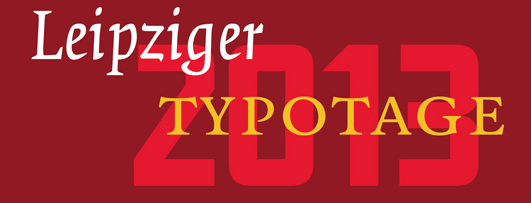
Noch vor weniger als zehn Jahren waren die typografischen Möglichkeiten in den Online-Medien begrenzt. Neue Geräte wie Smartphones, Tablet-PCs und e-Books und mobile Anwendungen wie Apps eröffnen der Typografie nun ungeahnte und vielfältige Möglichkeiten. Aber auch im Bereich der Schriftgestaltung hat das neue Jahrtausend schon einiges bewegt, junge Typografen denken und verwenden Schriften anders, ob in animierter Form, als digitale Redesigns historischer Vorbilder oder entwickeln ganz individuelle Designs für analoge und digitale Anwendungen.
Die verschiedenen Spielarten von Typografie im Spannungsfeld zwischen Print- und Onlinemedien heute wollen die 19. Leipziger Typotage näher beleuchten. Eingeladen sind acht renommierte Referenten, die über unterschiedlichste Projekte berichten und damit gleichzeitig die Trends in der Typografie im frühen 21. Jahrhundert beleuchten.
Die Referenten
Tim Ahrens, Berlin
David Fichtmüller, München
Friedrich Forssman, Kassel
Maurice Göldner, Leipzig
Christoph Knoth, Berlin und Halle/S.
Prof. Stephan Müller, Berlin und Leipzig
Henning Skibbe, Hamburg
Roman Wilhelm, Berlin
Ausstellung »Schrift im 21. Jahrhundert«
Den thematischen Rahmen der Typotage bildet die gleichnamige Ausstellung im Museum für Druckkunst Leipzig vom 10. März bis 5. Mai 2013. Präsentiert werden rund 90 internationale Schriftdesigns aus den letzten zehn Jahren. Ergänzt wird die Schau durch aktuelle Positionen in der Typografie aus Mitteldeutschland, eingeladen sind Absolventen der Kunsthochschulen Burg Giebichenstein Halle/Saale, Hochschule für Grafik und Buchkunst Leipzig und der Bauhaus-Universität Weimar.